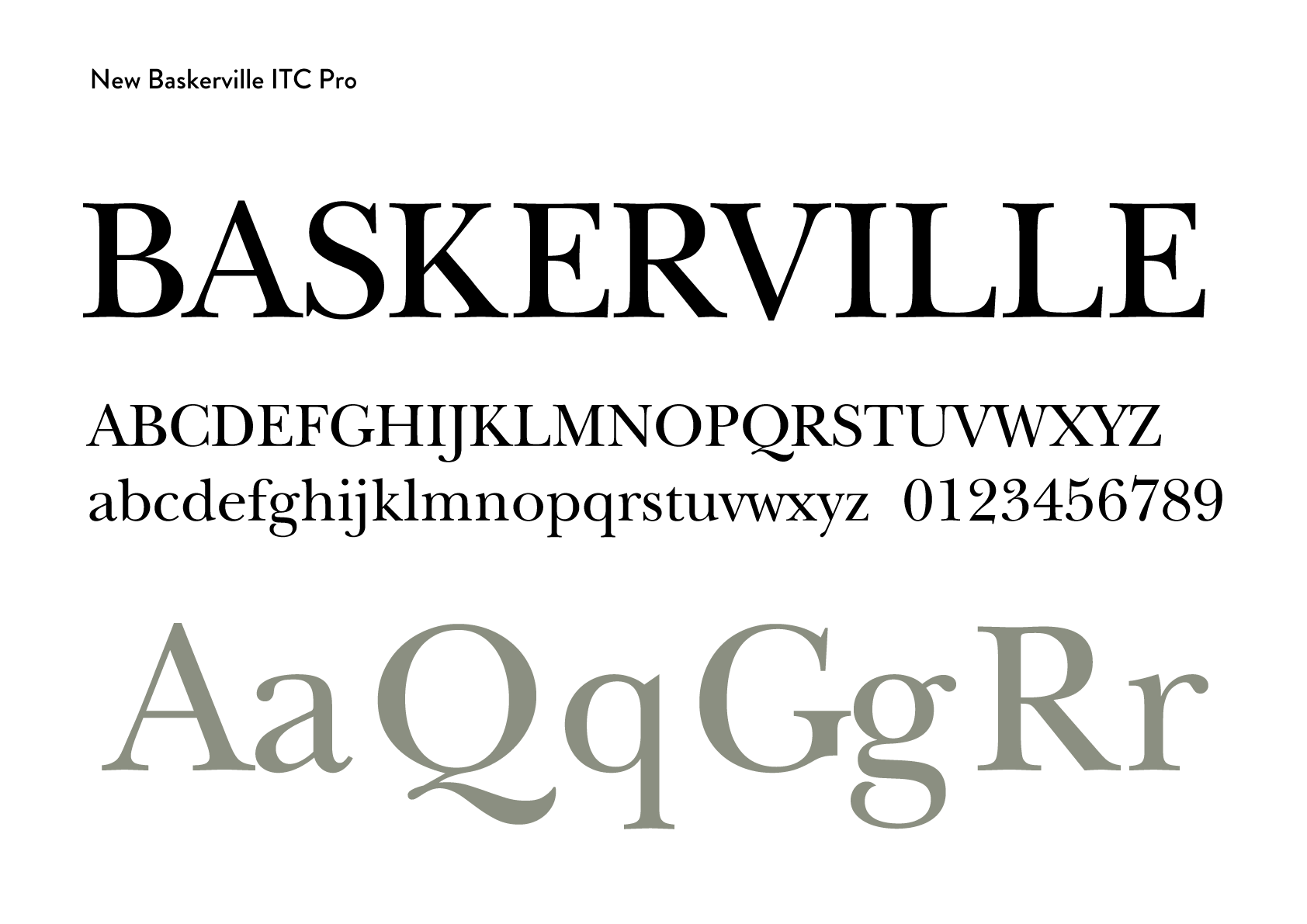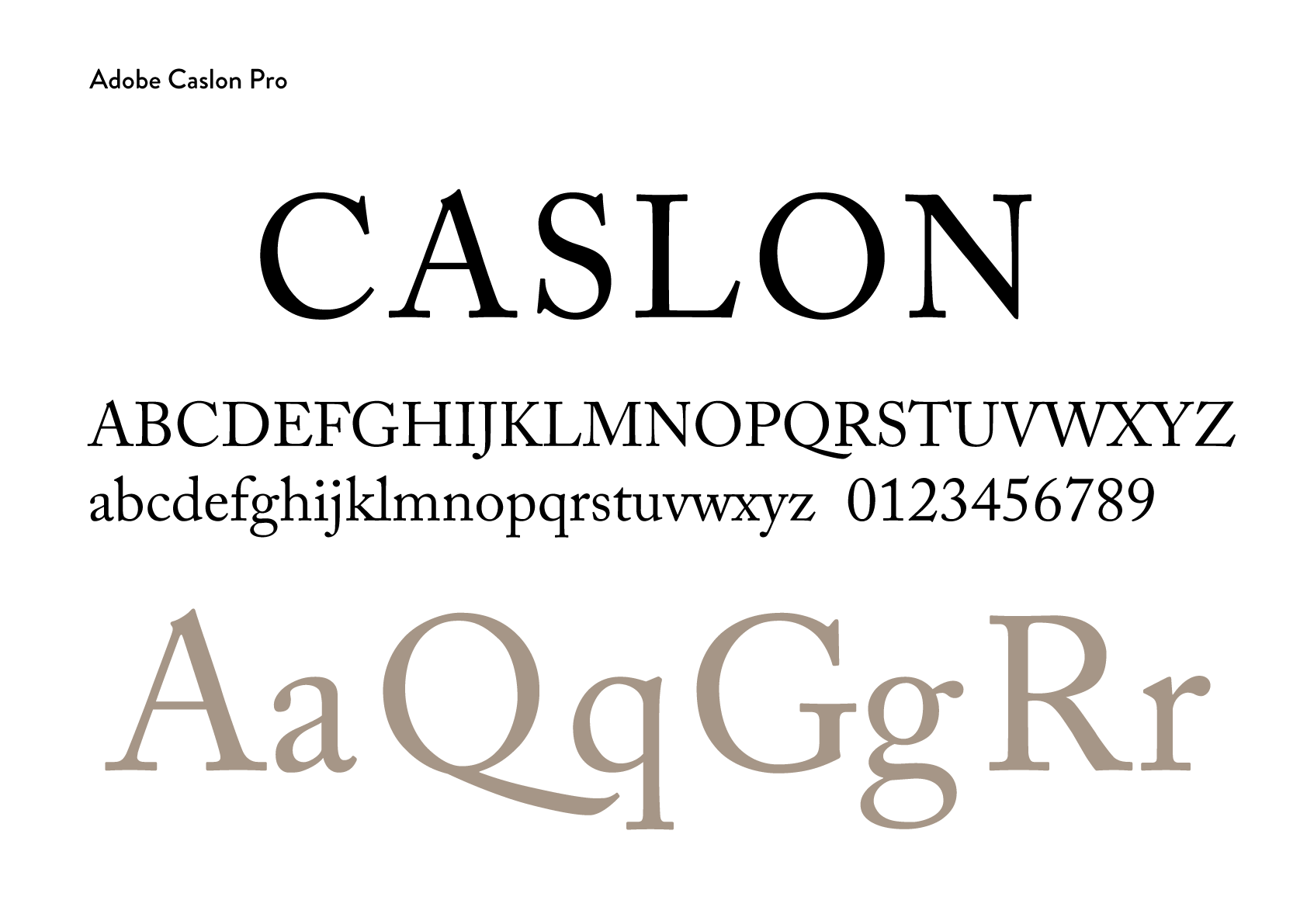
16世紀に暮らしたヨーロッパの紳士達が読む本の活字と21世紀に暮らす僕らがスクリーンで読む文字が数世紀の時を経てなお同じデザインであるということは、何かとても文化の奥深さを感じさせます。時代を超えて使われる普遍的なものとしての文字と変化し洗練されるタイプデザインの流れはタイプのもつ魅力でもあります。 クラシックとして残るフォントの面白さは古典としての美しさのみではなく、過去をたどり本質を残しつつ今の時代に合わせてゆくその過程にデザイナーの考え方や新な事実の発見や新な技術の登場などのドラマがあったりします。 ここでは、現在デジタルフォントとして使うことができる定番の活字について紹介して行きます。
The fact that the typeface used in books read by Europeans in the 16th century and the type we read on screens in the 21st century are still the same design centuries after the passage of time is something that makes us feel the depth of culture. The timeless universality of type and the changing, sophisticated flow of type design are also fascinating aspects of type. Here, we will introduce some of the standard typefaces that can be used as digital fonts today.
Garamond
- Country of Origin: France
- Clasification:Oldstyle Serif
- Designer:Cloud Graramon Robert Granjon
Garamond は16世紀のフランスでクラウド・ガラモンが製作した金属活字です。 ガラモンはルネッサンスの時代16世紀から17世紀にかけヨーロッパでもっとも影響のあった活字製造者です。 その活字は、オールドフェイスの代表格で、有機的な曲線の柔らかな印象、読み心地がよくクセのない普遍的な表情を持っています。古典的なタイプフェイスとして、優雅で詩的な印象を現代において世界中の人々に使われています。 現在のデジタルフォントとしてGaramondの名が冠されているものには幾つか流れがあります。 20世紀に入って 復刻された Garamondの活字は各ファウンダリーで異なっていました、とくにガラモンの死後に活躍したジャン・ジャノンJean Janonの活字が長らくガラモンのものとして扱われてきた影響でそれらを参照した幾つかのフォントはオリジナルのものと異なっています。またそれとは逆に、Garamondの名を冠していないSabonやGranjonなどオリジナルの活字をもとに設計されたものもあります。
Garamond is a metal type produced by Claude Garamond in 16th century France.Garamond was the most influential type maker in Europe during the Renaissance period of the 16th and 17th centuries.His type is representative of the old face, with its soft impression of organic curves and a universal look that is comfortable to read and free of peculiarities. As a classic typeface, it is used by people all over the world today for its elegant and poetic impression.There are several kind of current digital fonts bearing the Garamond name. In the 20th centuryThe Garamond typefaces that were reprinted differed from each other in the various foundries, especially the type of Jean Janon, who worked after Garamond’s death, and some of the fonts that referred to them differed from the originals because they had long been treated as Garamond’s. On the other hand, the Garamond typefaces that were reprinted in the early 20th century differed from the originals because they were based on the type of Jean Janon. On the contrary, some fonts were designed based on the original type, such as Sabon and Granjon, which do not bear the Garamond name.
Caslon
Caslonはイギリスの活字製造者ウィリアム・カスロンが18世紀前半に製作した金属活字です。 活字時代には、”When in doubt , use Caslon.”「迷ったらカスロンで組め」と言われるほでで、特に英語圏では多くのデザイナーのセリフフォントのデフォルトの選択肢となっています。特別な意図がない限りはCaslonで組むことが良いとされているほど定番中の定番です。 印象は、威厳があり安定感があります。読みやすく親しみのあるまさに定番というのにふさわしい幅の広さのある書体です。ベンジャミンフランクリンによって英国植民地時代のアメリカにもたらされ独立宣言書に使用された背景も伴って、アメリカをはじめ英語圏ではフォーマルから大衆的なものまで現在でも広い範囲で使われています。 このカスロンの活字をオリジナルにもつデジタルフォントのなかで、Adobe Caslonはとても忠実にその意図を反映していると評判です。そして、Big CaslonやCaslon 540 は見出し向きに作られており、本文より大きなサイズで使う場合に はこちらを合わせて使うことをお勧めします。
Caslon is a metal typeface produced by English type maker William Caslon in the first half of the 18th century.In the Movavle type era, it was said, “When in doubt, use Caslon.” It has become the default choice of serif fonts for many designers, especially in the English-speaking world. It is so standard that it is considered a good idea to use Caslon unless you have a special intention to use it.The impression is dignified and stable. The typeface is easy to read and familiar, and has a wide range that makes it a standard typeface. It was brought to the United States by Benjamin Franklin during the British colonial period and used in the Declaration of Independence, and is still widely used in the United States and other English-speaking countries for both formal and popular items.Among digital fonts based on the original Caslon typeface, Adobe Caslon has a reputation for faithfully reflecting the intent of the original. If you are using a font that is larger than the body text, we recommend that you use this font in conjunction with Big Caslon or Caslon 540.
Baskerville
Baskervilleは 18世紀の中盤にイギリスの ジョンバスカヴィルによって作られた金属活字です。 “the Strokes of your Letters being too thin and narrow , hurt the eye…” 「この極細のストロークが目に刺さる…」とまで言われるほど当時、型破りのデザインと文字の精密さにおいて完成度が高いものでした。バスカヴィルはその緻密な表現のために、金属活字のみならず、紙やインクを改良を重ねより美しい印刷を包括的に作り上げました。しかしながら、当時のイギリスの保守的な審美眼では受け入れられず、ベンジャミンフランクリンによってもたらされたアメリカやフランスで成功を収め、のちの世代に多大な影響を与えることになりました。それは、200年の歴史をもつ古典のオールドフェイスとこの後に出てくるモダンフェイスの間を取り持つトランジション過渡期書体と呼ばれて分類されています。 印象はとても優雅な気高さを感じさせ、新しさと伝統の両面を持ち、文芸などの書籍の本文に現在も使われています。 この活字をもとに作られたデジタルフォントは多くのファウンダリーからでています。ITC New Baskervilleなどが一般的ですが、妻の名をつけた、Mrs Evesのようにフェミニンなアレンジを加えたフォントなどもあります。
Baskerville is a metal typeface created by John Baskerville in England in the mid-18th century.“the Strokes of your Letters being too thin and narrow , hurt the eye…”was the most perfect example of the unconventional design and precision of the letters at the time. To achieve this precision, Baskerville made improvements not only in metal type, but also in paper and ink to create a more beautiful and comprehensive printing process. However, it was not accepted by the conservative British aesthetic of the time, and its success in the United States and France, where it was introduced by Benjamin Franklin, was to have a profound influence on later generations. It is classified as a transitional typeface, a typeface that takes up the space between the classic 200-year-old Old Face and the modern face that emerged later in this period.The impression is very elegant and noble, both new and traditional, and it is still used today in the text of books on literature and other subjects.Many foundries have produced digital fonts based on this typeface, most commonly ITC New Baskerville, but also some with a feminine twist, such as Mrs. Eves, named after Baskerville’s wife.
Bodoni
Bodoniは 18世紀後半にイタリアのジャンバチスタ・ボドニによって作られた金属活字です。 ボドニの活字はモダンフェイスと呼ばれ、それまで200年ほど使われてきたオールドフェイスに対して、より線幅のコントラストがつよく、より直線的、幾何学的な方向をもつデザインを生み出しました。ボドニはバスカヴィルの活字を研究することから多くのことを学び、それをさらに発展させる形で新な時代におけるデザインを完成させました。 モダンフェイスとオールドフェイスの大きな違いは、カリグラフィーによる人と道具が作り出す線の理想と、抽象的な幾何学的な線の理想の違いにあります。鋳造技術の進歩や近代化した社会の求めるものなどが絡み合って出来上がったとても近代的な美意識の強いものです。大きく方向性を示した転換点としての意味も強いのですが、文字としての洗練され、進化した美しさは普遍性を持って現代でも使い続けてられています。 この活字をもとに作られたデジタルフォントは、各ファウンダリーから出ています。とくにオリジナルを忠実に再現したものとして、Beauer Bodoni や ITC Bodoni が評価されています。
Bodoni is a metal type created by Giambattista Bodoni in Italy in the late 18th century.Bodoni’s type, known as modern face, was designed with more contrasting stroke widths and a more linear, geometric orientation than the old face that had been used for the previous 200 years or so. Bodoni learned a great deal from his study of Baskerville type, which he further developed into a design for a new era.The major difference between modern and old face is the difference between the ideal of the line created by man and his tools in calligraphy and the ideal of the abstract geometric line. It is a very modern aesthetic that is the result of a combination of advances in casting technology and the demands of a modernized society. Although the typeface has a strong meaning as a turning point that marked a major direction, its refined and evolved beauty as a typeface is still used today with universality.Digital fonts based on this typeface are available from various foundries. Beauer Bodoni and ITC Bodoni are particularly well regarded as faithful reproductions of the original.